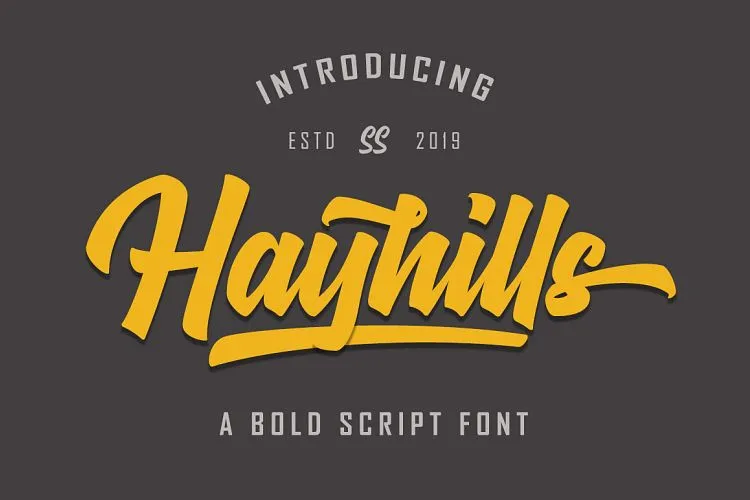
Hayhills Bold Script Font – Download Grátis
Essa fonte ‘Hayhills Bold Script Font’ é um design elegante para projetos criativos. Inspirada no estilo do escritório manuscrito moderno, ela traz uma dinâmica atemporal que se sobressai entre as demais fuentes. Ideal tanto para criar logotipos e assinaturas, como para texturas de cartas e etiquetas, ou até mesmo para artigos impressos e banners em formato grande. Ela é perfeita para aqueles projetos que buscam uma escrita fluida com um toque moderno, combinando rusticidade com elegância. Com sua tipografia robusta e sofisticada, o Hayhills Bold Script Font se destaca como a escolha ideal para qualquer projeto onde você deseja dar um toque único aos seus materiais de design impressos ou digitais.